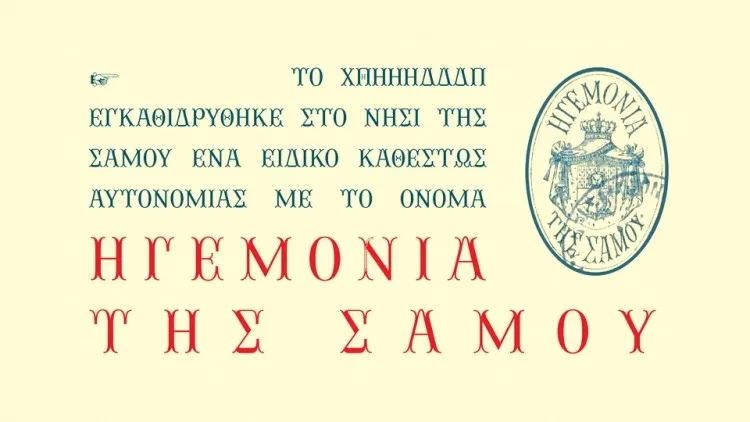
A Hegemonia Font é uma tipografia exibição criada pelo Backpacker inspirada nos traços de uma cartinha datilografada de 1900 que representa o escudo do Principado de Samos. Essa fonte vintage evoca a elegância e os detalhes meticulosos encontrados em letras antigas, projetadas para destacar texturas ricas e sutilezas gráficas. Perfeita para aplicações visuais requintadas, como contratos legais ou design editorial, a Hegemonia Font traz um toque de distinção que combina perfeitamente com o seu estilo vintage. Ideal tanto para aqueles que prezam por uma atmosfera retrô quanto pela elegância contemporânea, ela se destaca como uma opção excepcional em qualquer projeto design que valorize a qualidade e a história. Esta fonte de exibição da 99designs é uma escolha inegavelmente vencedora para designers amadores ou profissionais que desejam dar um toque sofisticado a seus trabalhos.